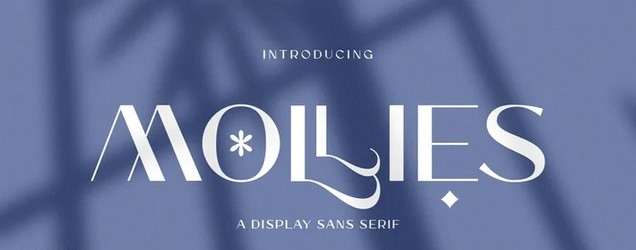
Название: Mollies Font (2021)
Mollies - элегантный и роскошный шрифт без засечек.
Модный и стильный, этот шрифт возвысит каждое ваше творение.
Название: Mollies Font (2021)
Mollies - элегантный и роскошный шрифт без засечек.
Модный и стильный, этот шрифт возвысит каждое ваше творение.